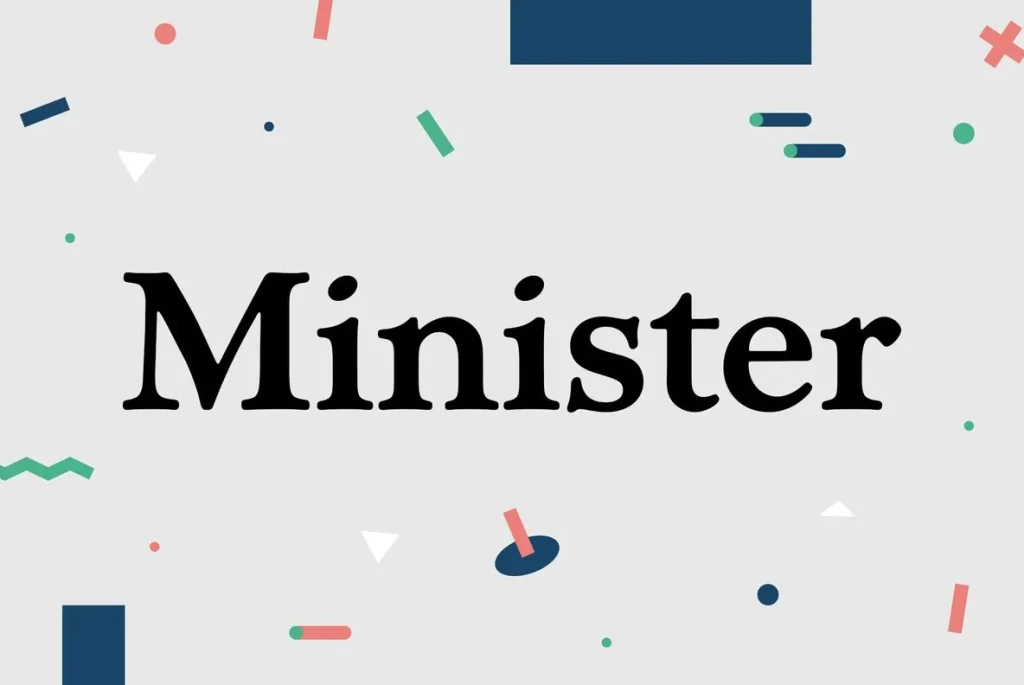
Kiểu chữ: Serif
Minister Font là một lựa chọn tinh tế cho những ai đang tìm kiếm một kiểu chữ sang trọng, đẳng cấp. Thuộc bộ font chữ có chân với đường nét sắc sảo và tỉ mỉ, phông chữ này phù hợp cho nhiều mục đích thiết kế như logo, tiêu đề, hoặc in ấn cao cấp. Bài viết này sẽ giúp bạn khám phá những điểm nổi bật của Minister Font và cách sử dụng nó hiệu quả trong các dự án sáng tạo.